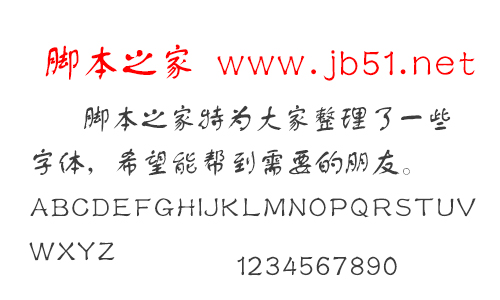
励字舒体简繁
励字舒体简繁是励字字库推出的一款个性艺术字体,庄而不板、甜而不俗的字体,包含简体字,繁体字及符号合计9540个,字形飘洒圆秀、弯弓盘马、沉雄峭拔、恣肆中见逸气,忽似壮士如牛,筋骨涌现。师古而不泥古,尊法而求新变。在结构上楷、行、隶、草、篆各取一分,在风格上颜、柳各取一分。欢迎喜欢励字舒体简繁字体的朋友前来下载使用。